Víš, tenhle smutek je můj. Ten bezradný.
Takhle přesně to mám.
A já najednou vidím v jeho jedenáctiletých očích opravdu záblesk smutku, tak jak ho prožívá.
Čtu si text karty, kterou si vybral.
Nevíte, odkud se bere a nerozumíte mu. Stojíte na místě, neschopni pohybu a ptáte se: „Co po mě chce?“
Kristiánku, a co radost? Kterou si vybereš?
Tahle, ta je moje.
Ze čtyř karet Radosti si bez váhání jednu vybere.
Radost vnitřní.
Je jako bílé světlo, které se šíří z vašeho středu a rozlévá se po celém těle. Neprojevuje se nahlas, většinou o ní ani nemluvíte, ale každý ji na vás pozná.
Já vlastně mám v sobe to světýlko, i když mám ten smutek. Proto vím, že ten smutek zase odezni. Že to světýlko je v tu chvíli malinké, ale za chvíli se zase rozsvítí… Vlastně mám v sobě takovej maják, kterej svítí pořád.
A já jsem viděla, jak se opravdu rozsvítil. Úplně mu to zvedlo náladu.
A tahle důvěra, ta se mi vůbec nelíbí (karta Nevěříci Tomáš – nikomu nevěří).
Důvěra je určitě takováhle.
A vybírá si kartu s jednoduchým patkovým fontem.
Určitě nebude taková kudrlinkatá, tu bych nikdy nevybral. U důvěry nechci žádné kudrlinky, ale přímost. Potřebuji mít jasno, bez pochybností, nic navíc. Abych se v tom vyznal. Ale u Naděje, to je jiná, ta může být kudrnatá, protože má spoustu variant!
Mami, já bych chtěl mít ty karty sám pro sebe. Pomáhají mi se v sobě vyznat.
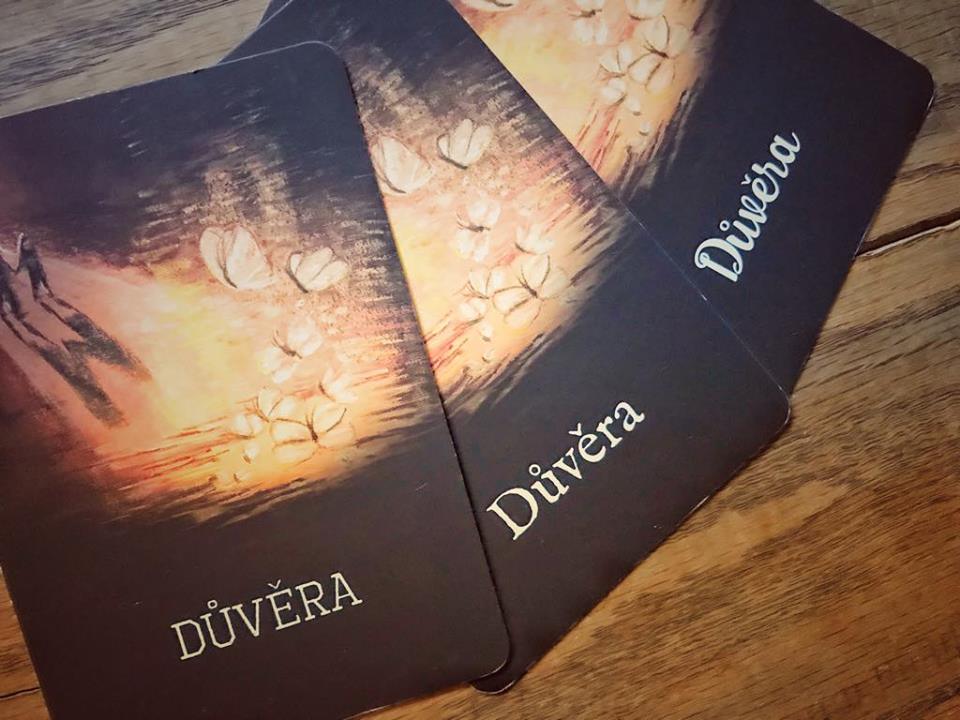
Tento rozhovor mi poslala maminka Zuzka. Právě dovezla domů karty Fontohrátky a prohlížela si je se svým synem. Kristiánek si vybíral karty podle písmenek. U každého tématu měl na výběr ze 4 různých fontů. Podvědomě sáhl vždy po tom, který dokázal popsat jeho pocity. Nic jsem nepřidala, nic jsem nezměnila. Není co. Ten rozhovor mě vtáhl do světa jedenáctiletého kloučka a jeho maminky. Do atmosféry důvěry a sdílení.
A najednou jsem tu vnitřní radost cítila taky. Byla tam už od ledna, kdy jsem se do karet pustila, ale až teď se rozzářila naplno. Funguje to. To, co jsem do karet vložila – touhu, aby děti i dospělí měli šanci spolu komunikovat o tom, co je v hloubi duše těší i trápí, aby to mohli bezpečně pustit ven a měli průvodce, který jim v tom pomůže, to se splnilo.
Tak ráda bych věděla, co se mu honí v hlavě
Když je dítěti pět, tak vám to řekne. Když mu je dvanáct a víc, už to není tak jednoduché. Řešíme úkoly, zkoušky, kroužky, povinnosti, ptáme se, jestli udělal to, co měl, jestli nezapomněl na to či ono…
Ale kdy najít čas, v tom každodenním kolotoči, popovídat si o tom, co cítí?
Možná při nenadálé chvilce důvěry večer před spaním, kdy jsme sami a nic na nás netlačí. Povídáme si a ze střípků historek a událostí, které dítě pustí, si skládáme jeho svět. Ale víme, jak vnímá důvěru, naději nebo domov? A ví to ono samo? Neví. Ale určitě to cítí.
Jsem si jistá, že většina dětí by neuměla slovy popsat to, co cítí (koneckonců ani většina dospělých). Hodí se jim most, který je k jejich pocitům dovede. A jestli je to font, který si vyberou na kartě, tak tím lépe, písmenka jsou v pohodě.
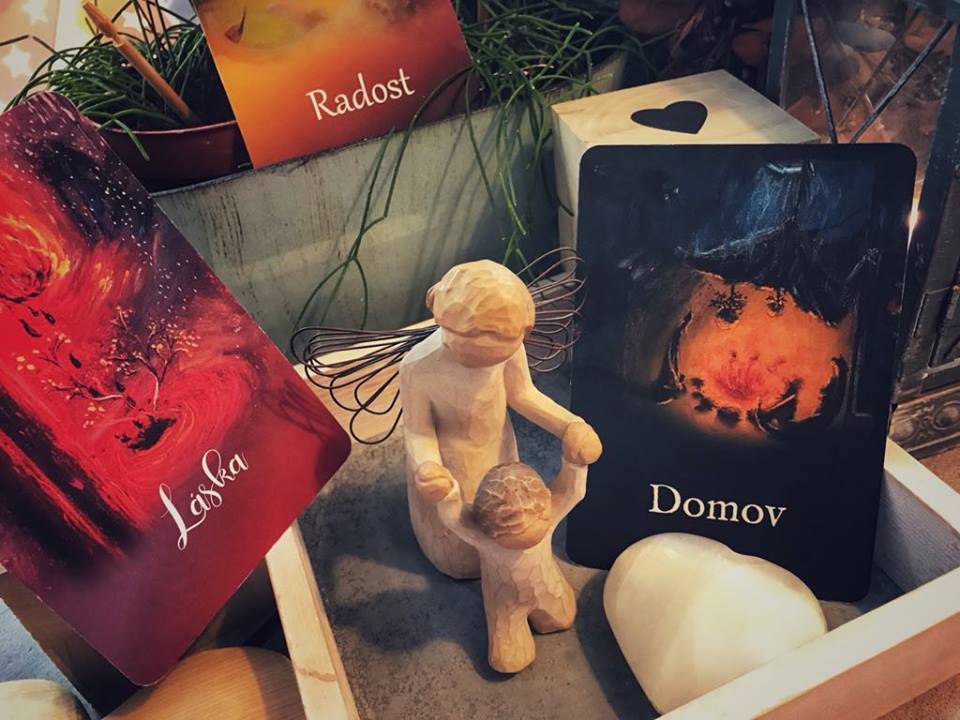
A vy se najednou dozvídáte věci, na které jste se nikdy nezeptali. Pocity, které byly doposud skryté za monitorem počítače, displejem mobilu nebo maskou individualismu, která je in. Dospívající děti a dospělí si ji nasazují a časem zjistí, že je pohodlná.
Při hraní s kartami škraboška padá a my můžeme naslouchat, sdílet a pochopit. A je úplně jedno, jestli:
- si povídáme s dítětem, nebo dospělým,
- nasloucháme, nebo mluvíme,
- jsme rodič, psycholog, terapeut nebo kouč
- s textem na kartách souhlasíme, nebo se nás dotkne.
Jsme spolu, v atmosféře důvěry a bezpečí.
Najednou pro vás jejich svět už není jednou velkou záhadou, ale přichází pochopení a porozumění.
Kristiánkovi posílám jeho vlastní balíček karet a nejraději bych ho poslala každému dospívajícímu dítěti, aby ho mělo pod polštářem. Pro chvíle, kdy se bude chtít vyznat samo v sobě. Pro chvíle, kdy bude chtít sdílet s mámou své pocity.